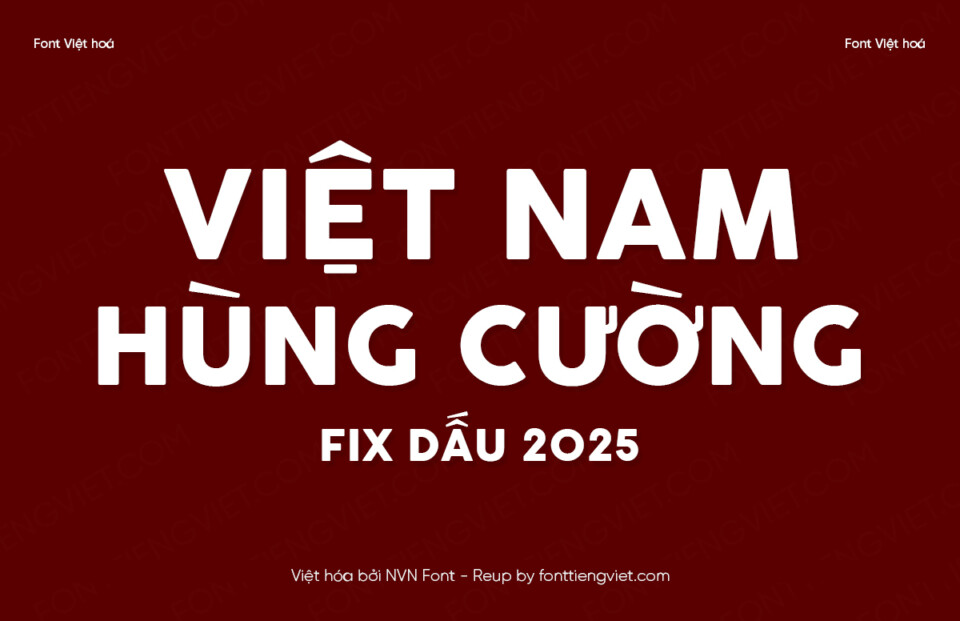
Font Việt hóa NVN Cocogoose Vintage 2 – Fix dấu 2025
NVN Cocogoose Vintage 2 – Fix dấu 2025 là lựa chọn lý tưởng nếu bạn cần một font Việt hóa phong cách vintage nhưng vẫn hiện đại, dễ đọc, cực kỳ bắt mắt. Bộ chữ có độ dày ấn tượng, form chắc, phù hợp thiết kế cần “đập vào mắt” như tiêu đề, logo, poster và bao bì.
Điểm nổi bật của Font Việt hóa NVN Cocogoose Vintage 2
• Việt hóa đầy đủ: hỗ trợ dấu tiếng Việt rõ ràng, hạn chế lỗi đặt dấu.
• Bản Fix dấu 2025: tinh chỉnh khoảng cách và độ cân đối khi gõ.
• Tính ứng dụng cao: dùng cho headline, branding, social post, thumbnail, banner.
Gợi ý dùng để “đúng chất” Cocogoose
Ưu tiên cỡ chữ lớn cho tiêu đề, kết hợp màu tương phản và tracking vừa phải để tạo cảm giác cổ điển, mạnh mẽ. Với nội dung dài, hãy dùng font khác cho body text và giữ Cocogoose cho phần nhấn.